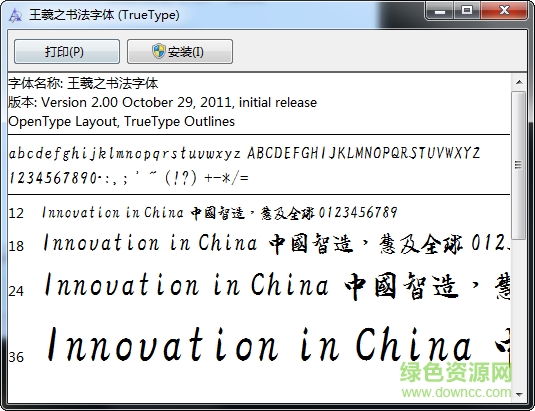
王羲之書法字體是大書法家王羲之的一款中文字體,王羲之的字非常好看,具有筆力雄勁,入木三分的特點,可用于海報設(shè)計、包裝設(shè)計以及字體設(shè)計等方面,歡迎下載使用。
王羲之擅長的書法非常多,其中又以行書、楷書、草書最引人注意。行書起源于楷書,是介于楷書、草書之間的一種書體,用筆簡潔,字體較放縱流動。行書乃后漢潁川劉德升所造,三國時著名書法家鐘繇、胡昭都善行書,在風(fēng)格上卻是胡肥鐘瘦。在晉朝時,更是將二人的書法制定為標(biāo)準(zhǔn)體。王羲之初習(xí)行書是以鐘繇為范本,其早年所書的《姨母帖》中,尚能明顯看出師法鐘繇的痕跡。但經(jīng)過摸索創(chuàng)造后,王羲之終于創(chuàng)出具有獨特風(fēng)韻、天質(zhì)自然、豐神蓋代的行書體,使行書藝術(shù)光照千古。王羲之的行書作品俊逸遒勁、神采飛揚、溫潤典雅、氣韻生動。著名的《蘭亭序》、《喪亂帖》、《快雪時晴帖》皆是其行書的代表作,此外還有《得示帖》、《孔侍中帖》等??瑫怯呻`書逐漸演變而來,始于漢末,在魏晉、南北朝時期得到了進一步發(fā)展,繼而長盛不衰。王羲之的楷書習(xí)自王廙和衛(wèi)夫人,與鐘繇的楷書一脈相承。鐘繇在書法史上首定楷書,至此始有古隸、今隸之分,夫以古法為隸,今法為楷可也。但他的楷書中,仍能看到狀似隸書中飛揚翻挑的筆勢。而王羲之的則在此基礎(chǔ)上加以創(chuàng)新。所書楷體瀟灑縱橫、何拘平正,楷書也由此進入今體階段。其楷書代表作有《樂毅論》、《黃庭經(jīng)》等。草書形成于漢代,為了書寫便捷而從隸書逐漸演化而來。最開始為字字獨立,筆勢不連貫的章草,東漢時期,在書法家張芝的推動下,又形成了可字字相連,更為自由便略的今草。王羲之在草書方面也頗有建樹,他的今草“一畫之間,變起伏于峰杪;一點之內(nèi),殊衄挫于豪芒”,狀若斷而還連,代表作有《十七帖》、《遠宦帖》、《初月帖》等。
王羲之的代表作,當(dāng)推于永和九年,王羲之50歲時所寫的《蘭亭序》。這年的三月初三為修祓禊日,時任會稽郡太守的王羲之與好友謝安、孫綽等四十余人,齊聚會稽山陰之蘭亭,是日天朗氣清、惠風(fēng)和暢,眾人在崇山峻嶺、茂林修竹、自然清麗的景色中,引以為流殤曲水,一觴一詠,暢敘幽情。王羲之微醺之際,趁著酒興一氣呵成寫下了千古名篇《蘭亭序》。此帖共28行,324字,其中有21個“之”字,卻各有變化無一雷同。通篇字體遒媚勁健、飄若浮云、矯如蛟龍;字態(tài)疏朗如清風(fēng)明月,抒發(fā)了晚年時王羲之對于生死無常的感慨。據(jù)說王羲之酒醒后曾經(jīng)連續(xù)重寫數(shù)篇,卻再也找不到當(dāng)時心手相應(yīng)、意隨筆轉(zhuǎn)的感覺,所寫皆不及原作。王羲之自己也感嘆說“:此神助耳,何吾能力致?!倍短m亭序》也被書法界奉為中華第一行書。唐太宗李世民千方百計得到此帖后,愛不釋手,將其作為陪葬品埋入昭陵,世間從此便無《蘭亭序》。
王羲之的《蘭亭集序》為歷代書法家所敬仰,被譽作“天下第一行書”。王兼善隸、草、楷、行各體,精研體勢,心摹手追,廣采眾長,備精諸體,冶于一爐,擺脫了漢魏筆風(fēng),自成一家,影響深遠
。其書法平和自然,筆勢委婉含蓄,遒美健秀,世人常用曹植的《洛神賦》中:“翩若驚鴻,婉若游龍,榮曜秋菊,華茂春松。仿佛兮若輕云之蔽月,飄飖兮若流風(fēng)之回雪?!币痪鋪碣澝劳豸酥臅ㄖ馈髡f王羲之小的時候苦練書法,日久,用于清洗毛筆的池塘水都變成墨色。后人評曰:“飄若游云,矯若驚龍”、“龍?zhí)扉T,虎臥凰閣”、“天質(zhì)自然,豐神蓋代”。有關(guān)于他的成語有入木三分、東床快婿等,王羲之書風(fēng)最明顯特征是用筆細(xì)膩,結(jié)構(gòu)多變。
王羲之書法影響了一代又一代的書苑。唐代的歐陽詢、虞世南、諸遂良、薛稷、和顏真卿、柳公權(quán),五代的楊凝式,宋代蘇軾、黃庭堅、米芾、蔡襄,元代趙孟頫,明代董其昌,這些歷代書法名家對王羲之心悅誠服,因而他享有“書圣”美譽。